Font Monopoli
Diterbitkan: 2023-04-01Faktanya, saya ingin berbagi dengan Anda kekhawatiran tentang judul blog ini atau pertanyaan yang mungkin dimiliki pengguna tentangnya: Pernahkah Anda bertanya-tanya font apa yang digunakan pada game Monopoli yang terkenal itu?
Poster permainan papan Monopoli adalah bagian dari budaya pop yang telah menjadi identik dengan permainan papan klasik Monopoli Parker Brothers sampai pada titik di mana ribuan orang di seluruh dunia sekarang akrab dengan poster film monopoli yang terkenal itu sebagai hasil dari penyebarannya yang luas. kepopuleran.
Untuk membedakan poster dari yang lain, logo Monopoly adalah salah satu elemen utama yang membedakan poster dari yang lain dan membuatnya lebih berkesan karena fontnya yang unik.
Tujuan artikel ini adalah untuk membahas sejarah dan asal usul font Monopoly, serta cara mendapatkan font tersebut dan cara menggunakannya dalam desain Anda sendiri dengan kemampuan terbaik Anda.
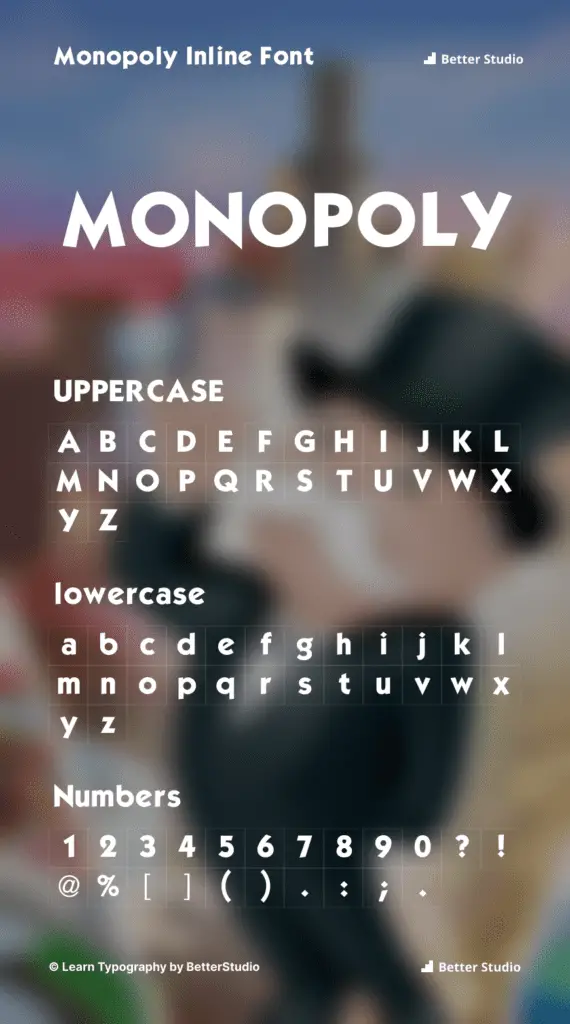
Monopoli Menggunakan Font Apa?
Untuk membuat logo Monopoly, kami menggunakan font bernama Kabel , yang memiliki tekstur berbeda dan gaya vintage menjadikannya pilihan ideal tidak hanya untuk pembuatan logo tetapi juga untuk pengembangan judul, judul, dan sampul buku.
Alternatif dan Gaya Font Mirip dengan Kabel
Berikut adalah daftar lima font alternatif untuk Kabel yang memiliki desain dan penggunaan yang sama:
- Jenis huruf Helvetica Neue Light
- Jenis huruf Arial Rounded
- Jenis huruf Futura PT Bold
- Font biasa Gotham Pro
- Font Akzidenz Grotesk
Ini adalah font yang sangat serbaguna yang dapat digunakan untuk berbagai proyek. Ini dapat digunakan untuk membuat logo, poster, atau situs web. Ini pada dasarnya berfungsi untuk setiap proyek terlepas dari apakah itu untuk penggunaan pribadi atau perusahaan.
Siapa Nama Perancang Font Monopoli?
Sebagai ahli kaligrafi, perancang huruf, dan guru, Rudolf Koch adalah orang di balik jenis huruf Kabel. Lahir di Nuremberg, Jerman pada tahun 1876, Koch adalah salah satu penata huruf pertama di abad ke-20.
Pada tahun 1930, dia menciptakan font Kable, dan meskipun font kabel mendahului font lain yang dia kembangkan, termasuk keluarga font Kabel, ini mungkin contoh paling awal dari karya tipografinya di mana dia terlihat jelas.
Gim papan klasik yang pertama kali ditemukan oleh Parker Brothers pada tahun 1935, Monopoli telah menjadi salah satu gim paling populer dan ikonik sepanjang sejarah karena kesederhanaan dan aksesibilitasnya.
Tidak ada keraguan bahwa desain aslinya didasarkan pada logo kereta api yang dapat dikenali, namun edisi selanjutnya juga menggunakan font Kabel klasik yang dikaitkan dengan perusahaan.